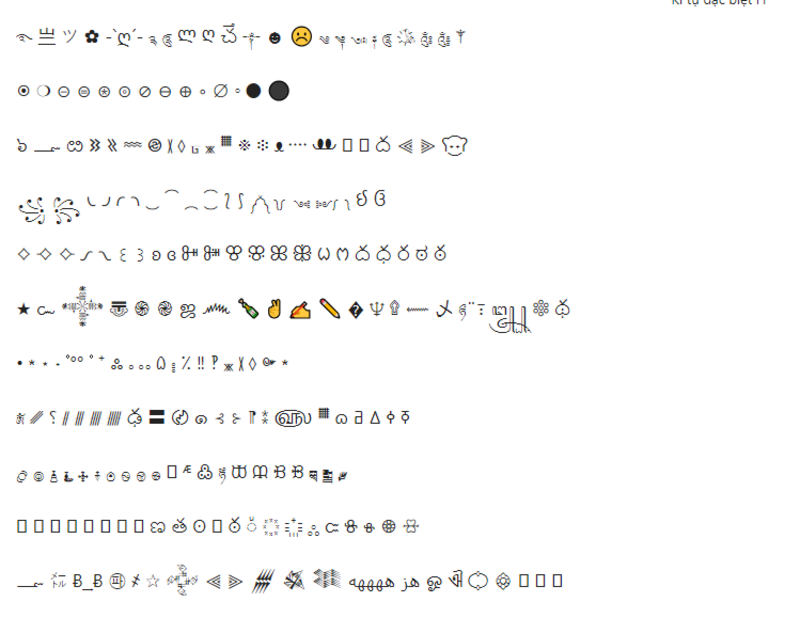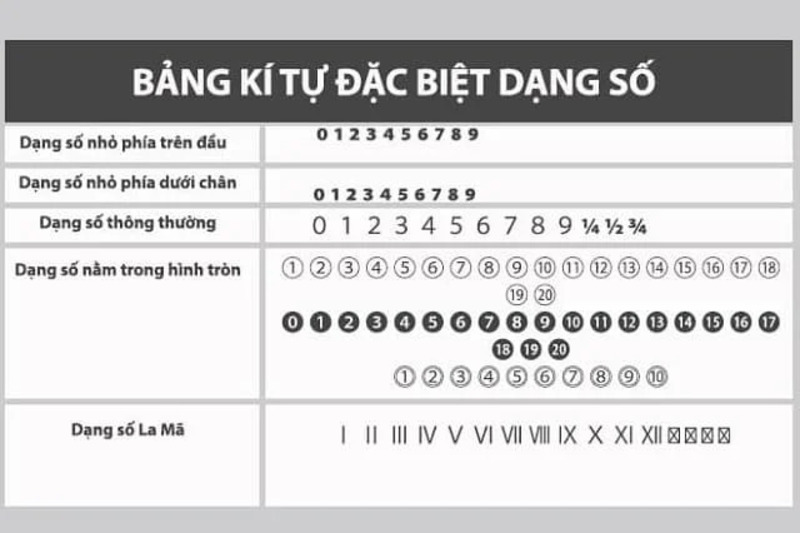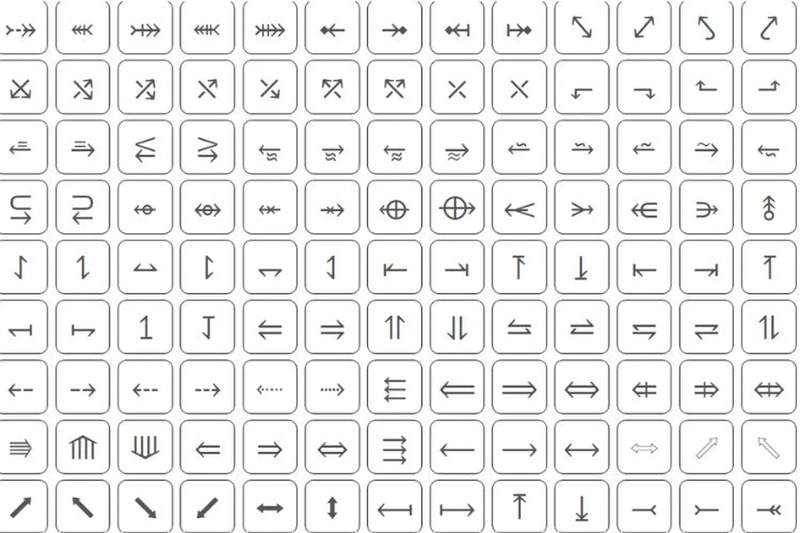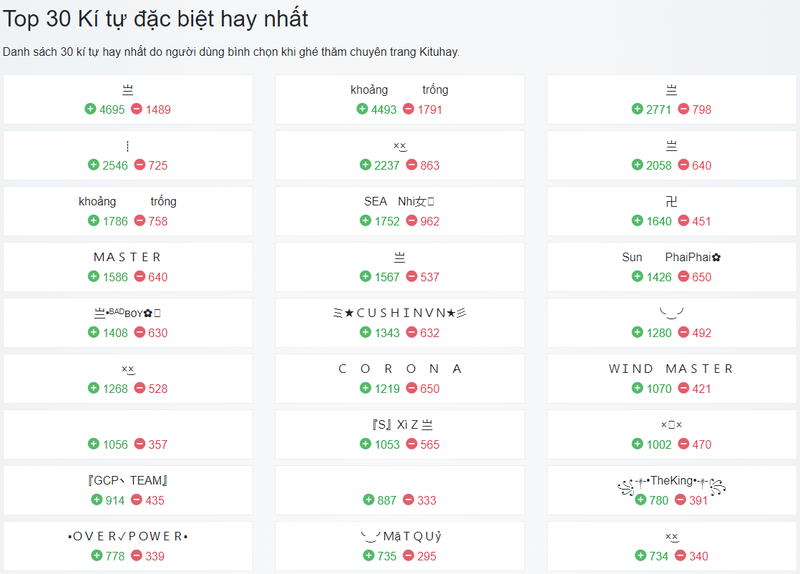
+ 700 Kí tự đặc biệt cho Truy Kích đặt tên nhân vật cực ngầu
Bài viết này sẽ cung cấp bộ sưu tập kí tự đặc biệt cho Truy Kích đầy đủ nhất bao gồm mẫu kí tự đặc biệt Truy Kích đẹp và ấn tượng với các biểu tượng chiến đấu, chữ số cách điệu, mặt cười dễ thương, mũi tên độc đáo và kí tự tiếng Nhật-Hàn-Trung. Mobifonts cũng sẽ hướng dẫn chi tiết về cách đổi tên nhân vật với kí tự cho Truy Kích nhanh chóng và giải đáp các thắc mắc phổ biến về kí tự Truy Kích trong game.
Các mẫu kí tự đặc biệt cho Truy Kích hiện nay rất đa dạng và phong phú, được chia thành nhiều nhóm khác nhau để phù hợp với từng phong cách game thủ. Dưới đây là những kí tự đặc biệt trong Truy Kích được yêu thích nhất bao gồm biểu tượng chiến đấu mạnh mẽ, chữ số cách điệu độc đáo, mặt cười dễ thương, mũi tên sắc nét và các tên kí tự đặc biệt Truy Kích từ các ngôn ngữ châu Á.
Kí tự biểu tượng chiến đấu là những kí tự đặc biệt cho Truy Kích, thể hiện tinh thần mạnh mẽ và sức chiến đấu. Những biểu tượng này thường được các game thủ “máu chiến” lựa chọn để tạo nên những cái tên mạnh mẽ và đầy khí chất. Vậy những ký tự đó là gì? Xem ngay dưới đây:
Kí tự đặc biệt Truy Kích dạng chữ, số cách điệu là những ký tự Unicode được biến tấu từ bảng chữ cái và chữ số thông thường, giúp tạo nên tên nhân vật độc đáo, đậm chất game thủ trong game Truy Kích. Những kí tự này mang ý nghĩa cá nhân hóa, thể hiện phong cách riêng, tạo dấu ấn mạnh mẽ và dễ nhận diện trong thế giới ảo. Dưới đây là bảng các kí tự, mã Unicode và tên Unicode để bạn tham khảo và sử dụng trong game Truy Kích.
Kí tự Truy Kích hình mặt cười dễ thương là tập hợp các biểu tượng cảm xúc dạng mặt cười được sử dụng để trang trí tên nhân vật, tiểu sử hoặc tin nhắn trong game Truy Kích. Những kí tự đặc biệt Truy Kích này mang ý nghĩa tạo cảm giác thân thiện, vui nhộn và thể hiện sự hài hước, cá tính riêng của người chơi. Dưới đây là bảng các kí tự, mã Unicode và tên Unicode để bạn có thể sử dụng trong Truy Kích.
Kí tự đặc biệt cho Truy Kích hình mũi tên là tập hợp các ký hiệu biểu tượng hướng đi, thường được dùng để trang trí tên nhân vật hoặc tạo hiệu ứng thị giác trong game. Những kí tự này không chỉ giúp định hướng, nhấn mạnh thông tin mà còn thể hiện sự sáng tạo và phong cách riêng của người chơi. Khám phá ngay bảng kí tự đặc biệt trong Truy Kích dưới đây để thêm phần nổi bật cho tài khoản Truy Kích của bạn!
Kí tự đặc biệt cho Truy Kích đã trở thành một phần không thể thiếu trong việc tạo ra những tên nhân vật độc đáo và ấn tượng. Việc sử dụng kí tự không chỉ giúp tên nhân vật nổi bật hơn mà còn thể hiện cá tính và phong cách riêng của từng game thủ. Tuy nhiên, điều quan trọng là phải biết cách kết hợp kí tự đặc biệt trong Truy Kích một cách hài hòa và phù hợp, tránh lạm dụng để đảm bảo tính thẩm mỹ và khả năng tương thích. Hy vọng bộ sưu tập kí tự đặc biệt cho Truy Kích của MobiFonts sẽ giúp bạn tạo ra những tên nhân vật cực ngầu và thu hút.